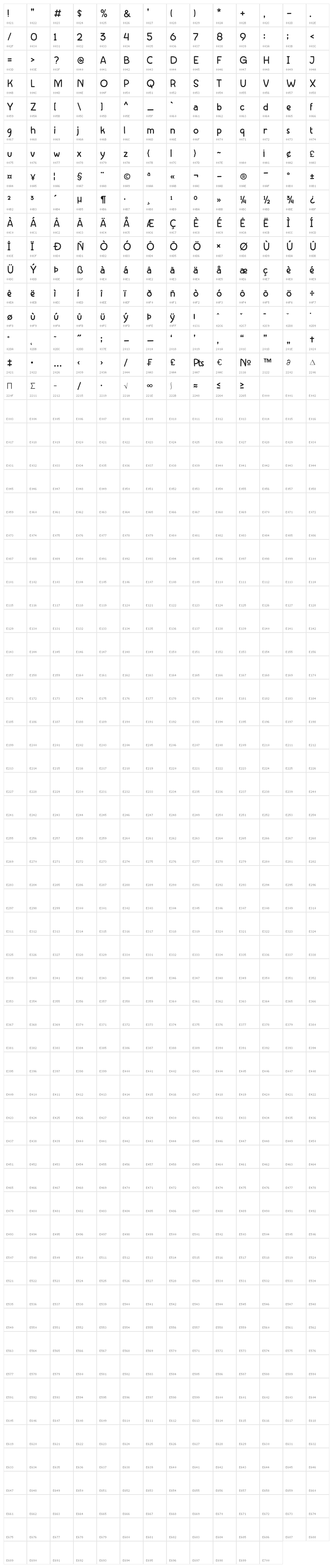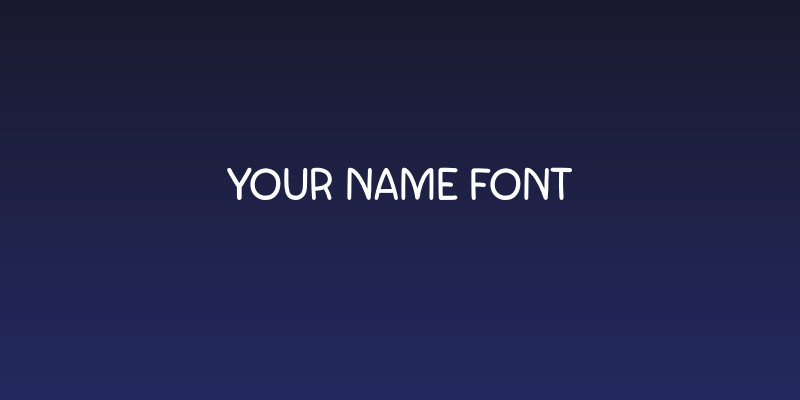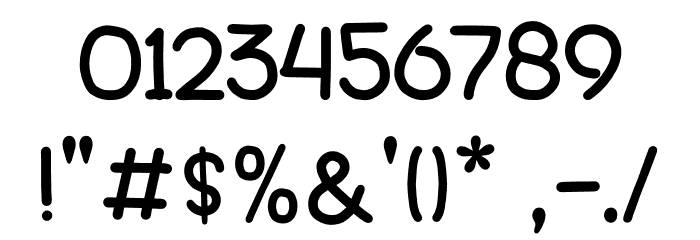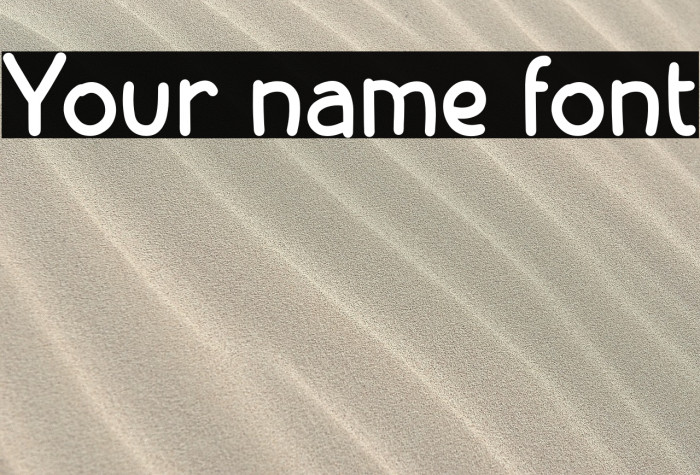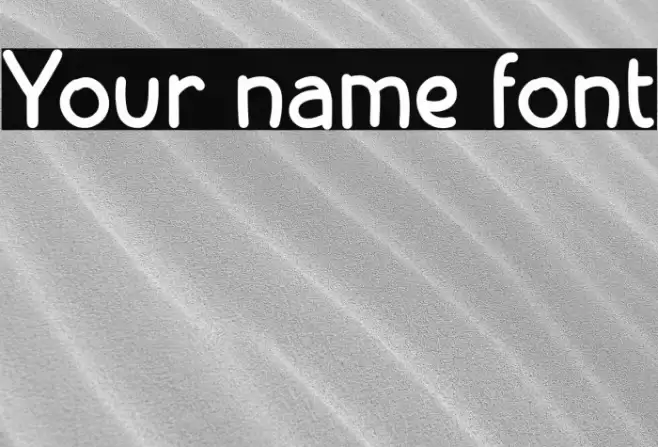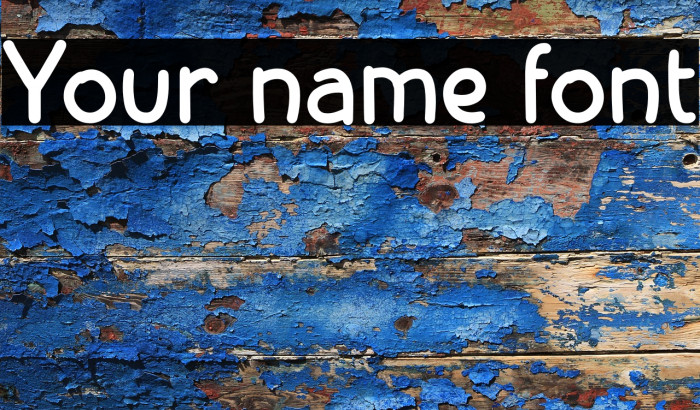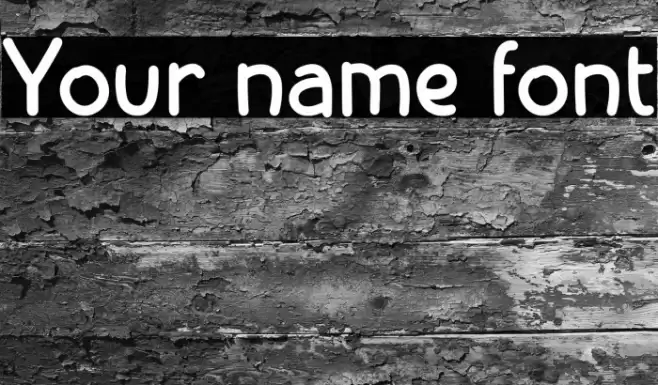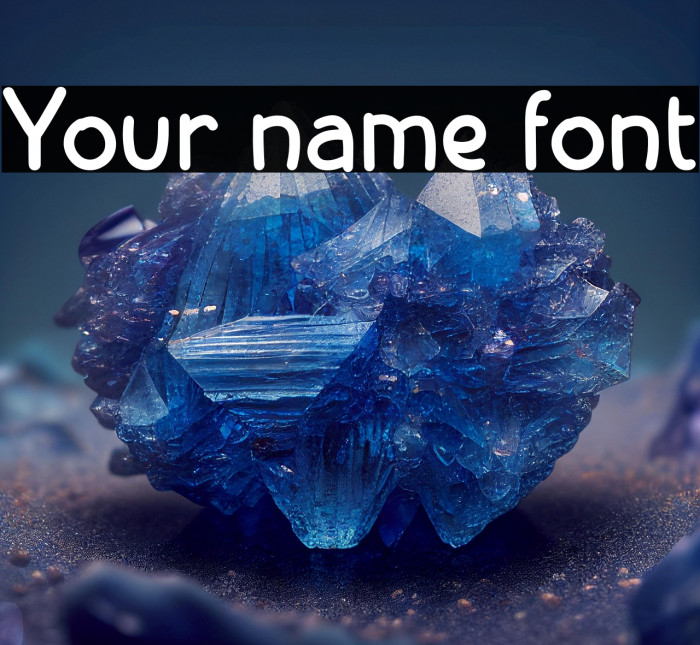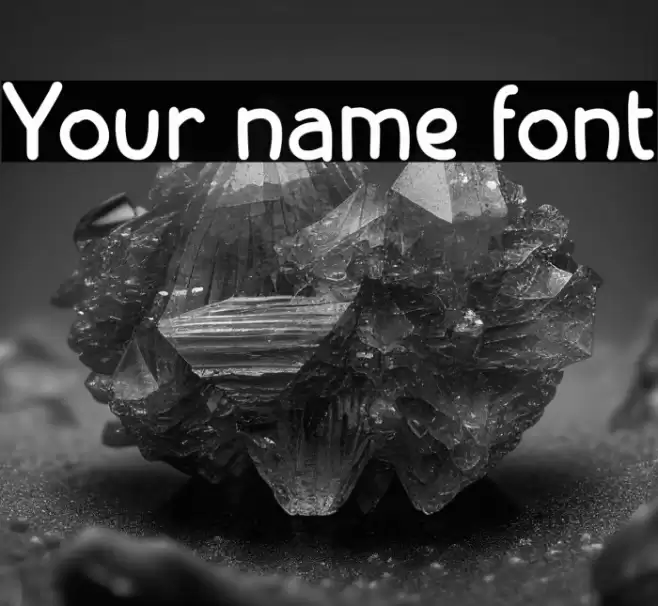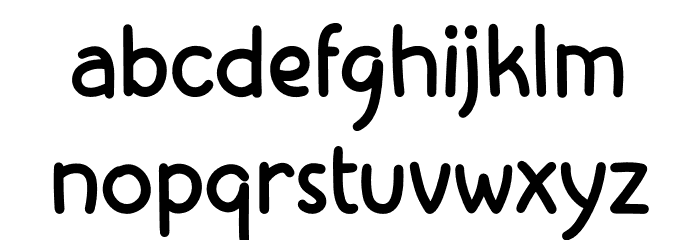
Your name font Font
| Caz de utilizare | Headlines, Logos, Informal Text |
| Proiecte propuse | Ideal for children's books, educational materials, playful branding, and casual invitations. |